(Share) Tìm hiểu về font
Font (kiểu chữ), tiếng Việt - phông chữ - là một tài nguyên vô cùng quan trọng trong việc tạo ra một bức hình đẹp, tầm quan trọng chỉ ngay sau stock dùng edit hoặc design thôi. Nhiều người hay nhầm font với Typeface nhưng thật ra font chỉ là một phần của Typeface.
Thật ra lý thuyết thì ai cũng có thể tự tìm hiểu trên google nên Thu chỉ nói theo quan điểm của mình. Có mấy kiểu font sau: (theo bộ chữ cái abc)
Serif: (có chân)
Serif typeface là loại typeface có các nét phụ ở cuối các nét chính của chữ. Serif dịch nôm na ra là chân của chữ. Một số kiểu chữ serif điển hình là Time News Roman và Garamond.
Thằng này còn có một anh em đồng bọn nữa là Slab - chữ có chân lớn.
Theo mình thì font serif thường được dùng làm text phụ hoặc tên tác giả của tấm hình edit, nói chung là những phần phụ ấy. Trong trường hợp nó đẹp như font dưới đây thì có thể được dùng làm text chính :D
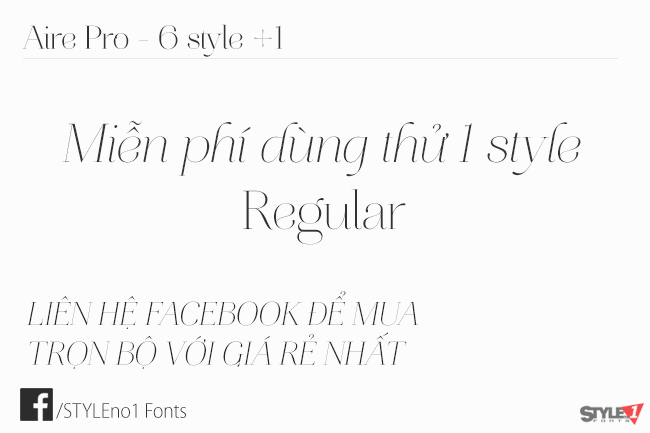
Sans- serif:
Trái ngược với Serif, Sans- serif là font không có chân, tiêu biểu là Arial.
Theo mình thì Sans- serif cũng thường được dùng làm text phụ và tên tác giả, trừ khi nó đẹp mới dùng làm text chính. Nhưng font Sans- serif đẹp thì hay là lai giữa Script và Sans- serif như dưới đây:
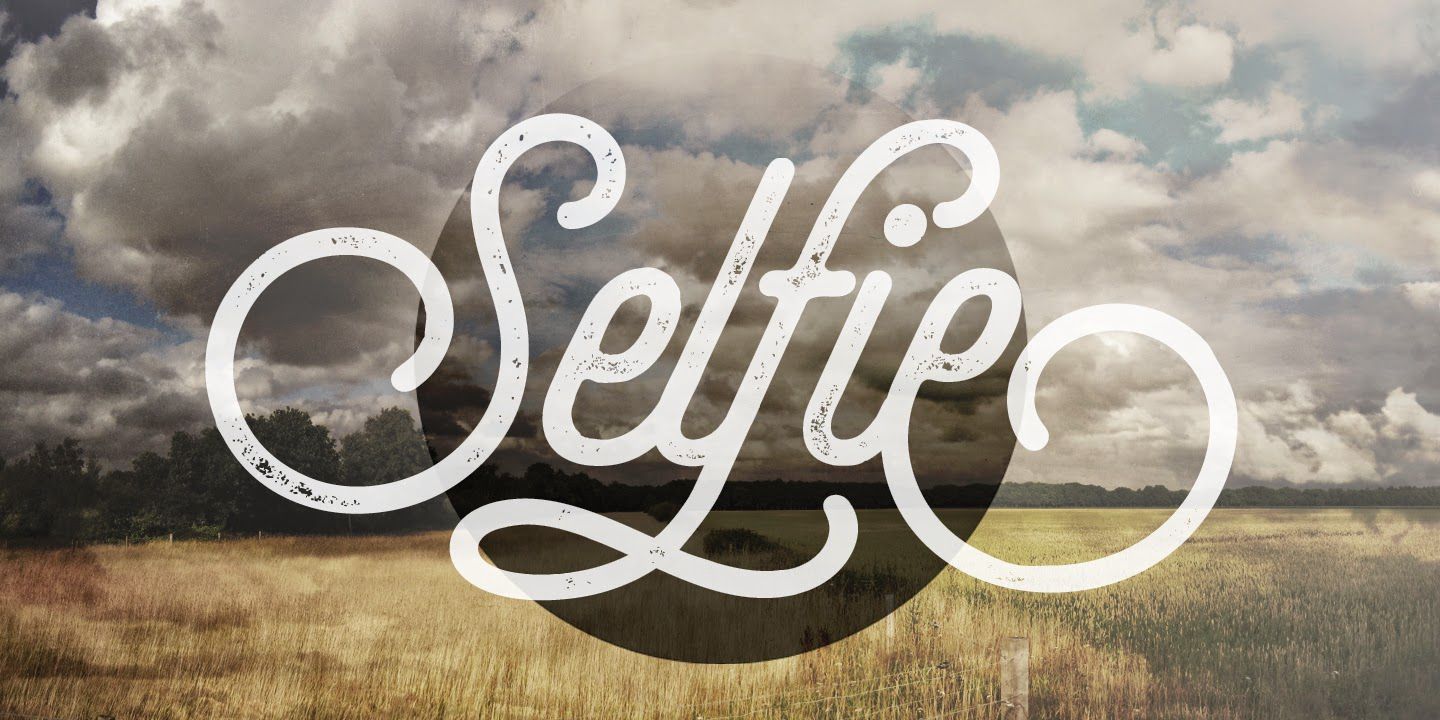
Vậy Script là gì?
Script:
Script (font mềm) là kiểu font bắt chước chữ viết tay nhưng nó thường nghiêng về hướng mềm mại, uốn lượn mỹ miều và có nhiều nét chứ không hoàn toàn là Hand-writing (Hand-writing vẫn có font trông cứng cáp). Người ta ít khi dùng Script trong phần thân văn bản vì nó gây rối mắt.
Một font script bay nhảy:
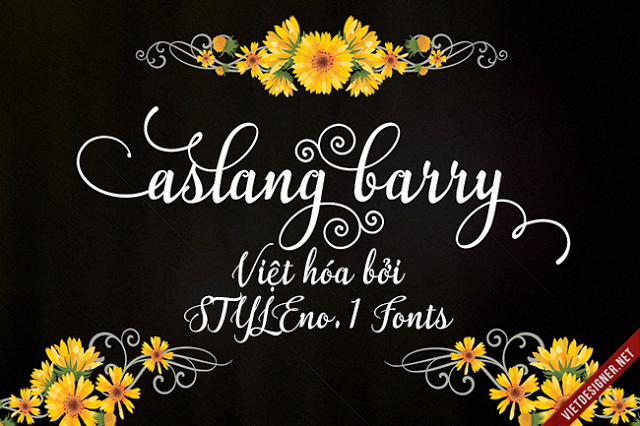
Theo Thu thì phần lớn font Script đều được dùng làm text chính cho bìa truyện hoặc những phần quan trọng trong banner hay quotes.
Các photo editor hoặc designer nên hạn chế dùng kiểu font này cho text phụ hoặc tên tác giả vì một là nó sẽ gây rối mắt, hai là do text phụ hoặc tên tác giả thường rất nhỏ nên nếu dùng font mềm thì khiến chữ chìm, không đọc được.
Tất nhiên là nếu bạn biết kết hợp khéo léo thì bức hình vẫn sẽ ổn nhưng nên hạn chế lại. Nhất là khi chúng ta edit ảnh chưa thành thạo thì đừng lạm dụng font mềm.
Hand writing:
Hand writing cũng là kiểu chữ bắt chước chữ viết tay, cũng hoa mỹ uốn lượn giống như Script nhưng nét thường mỏng hơn và cũng có kiểu hand writing cứng nữa.
Tương tự như Script, hand writing thường được dùng làm text chính và những phần quan trọng chứ không hợp với phần phụ và nhỏ.
Một font Hand wrting cứng:
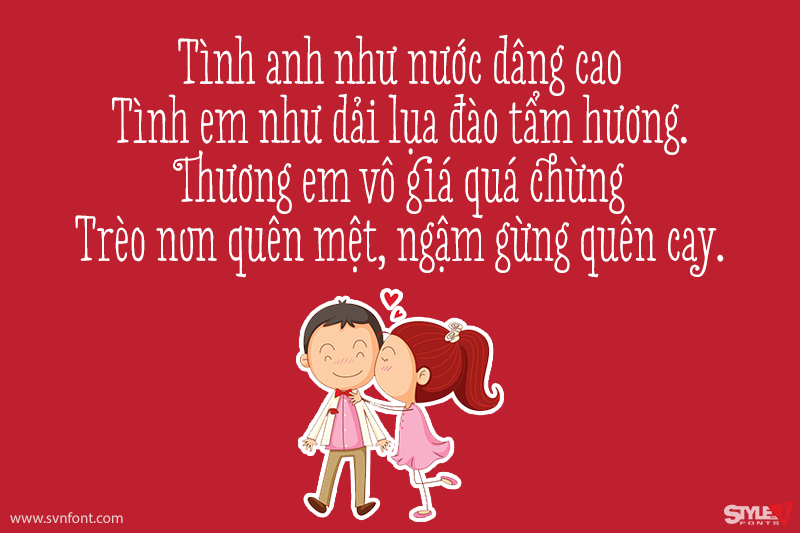
Brush:
Brush là kiểu font giống như dùng chổi viết nên vậy, có những cái vệt vệt và thường là font cứng. Có những font brush khá dày nữa.
Về công dụng của brush thì có lẽ chỉ nên dùng cho text chính và những phần quan trọng thôi, mình có thể nói là từ hồi gia nhập wattpad đến giờ mình chưa thấy ai edit ảnh mà dùng brush font làm text phụ cả, chắc là vì nó không phù hợp và phá bìa trầm trọng .__.
Một font brush:
Đó là các kiểu font cơ bản, thích hợp với photo editor/ designer và được tìm kiếm nhiều nhất. Ngoài ra còn có một số kiểu font khác như Symbol, Ornament (có ký tự đặc biệt); Display (hiện đại, phá cách); Vintage (cổ điển), Thư pháp (cổ trang)...